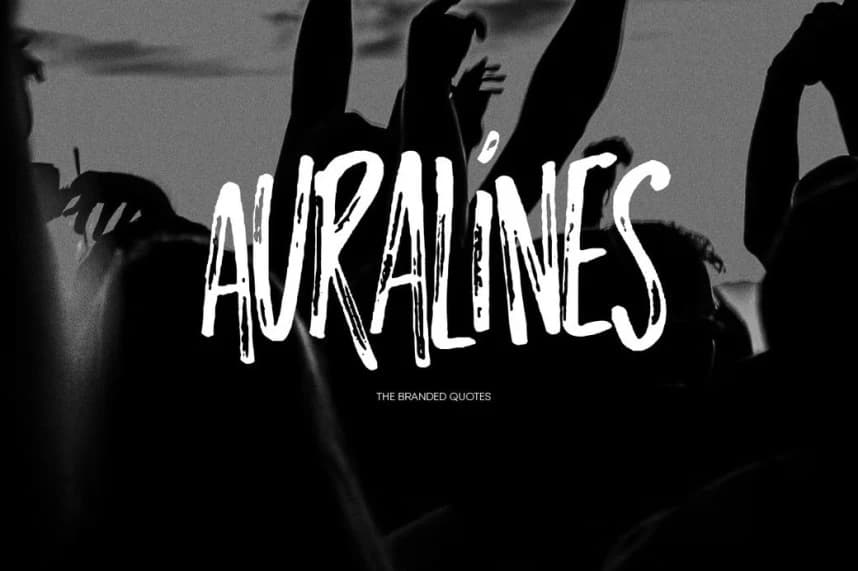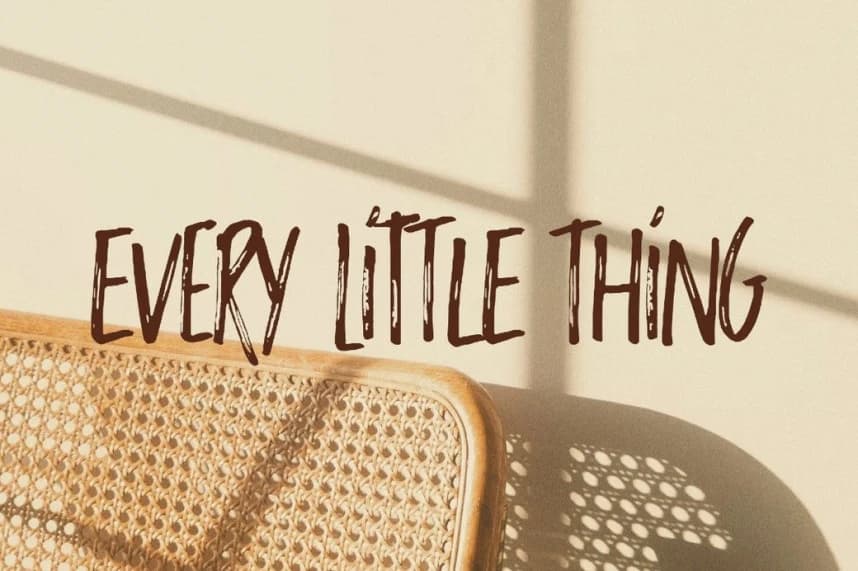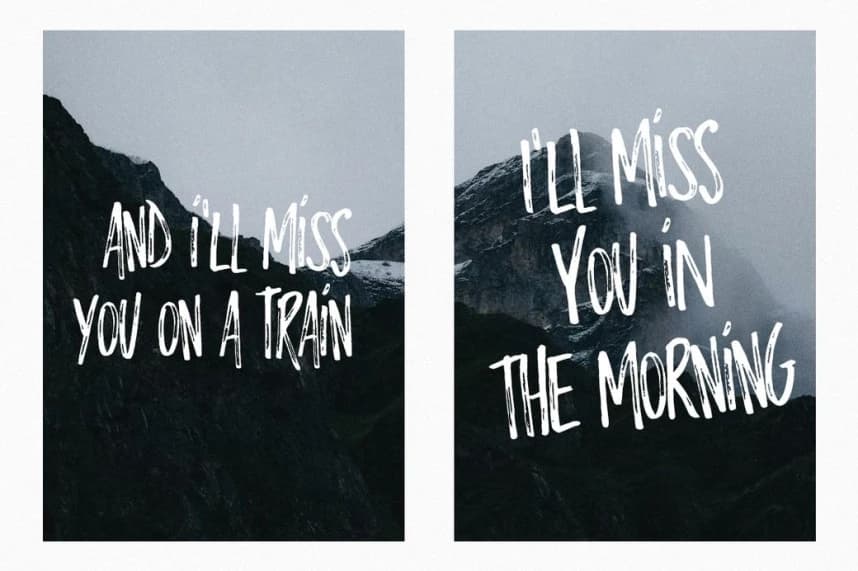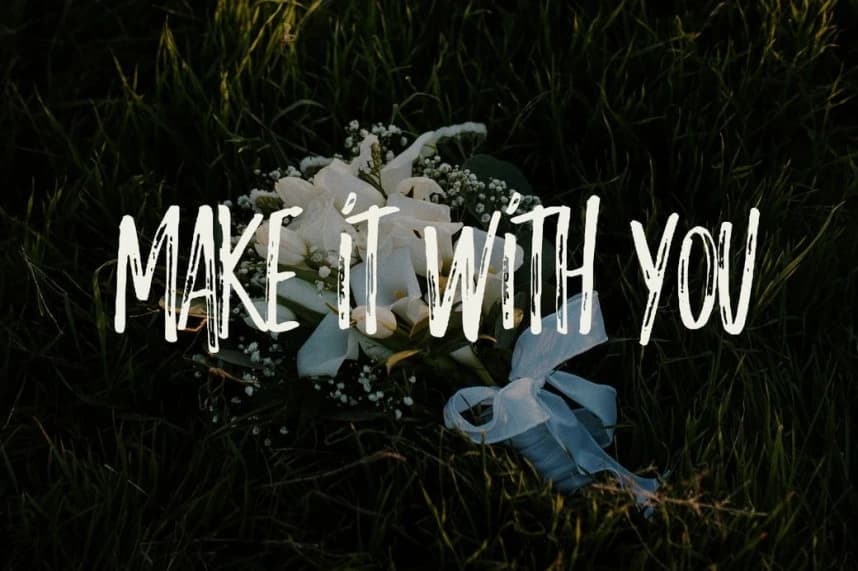
Auralines Brush Font
Auralines Brush Font, ifadeli ve doğal görünen projelerin ihtiyaçlarını karşılamak üzere tasarlanmıştır; ancak fırça darbelerindeki abartılara yer vermez. Klasik fırça fontlarımızdan ilham alır ve okunabilir serbest el çizgilerinin modern dokunuşuyla zenginleşir.
Auralines Brush Font, ifadeli ve doğal görünen projelerin ihtiyaçlarını karşılayacak şekilde tasarlanmıştır; ancak fırça darbelerindeki abartıları barındırmaz. Klasik fırça fontlarımızdan ilham alır ve okunabilir serbest el yazısı darbelerinin modern bir dokunuşuna sahiptir.